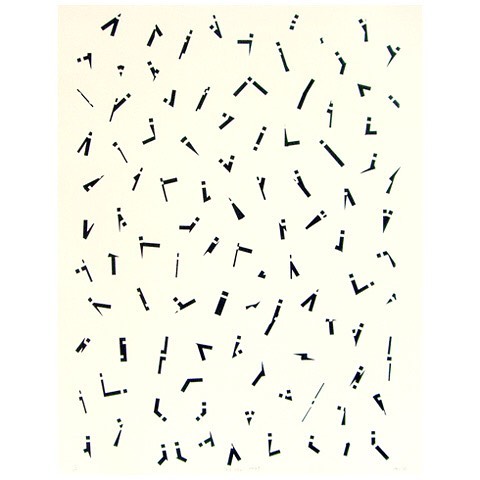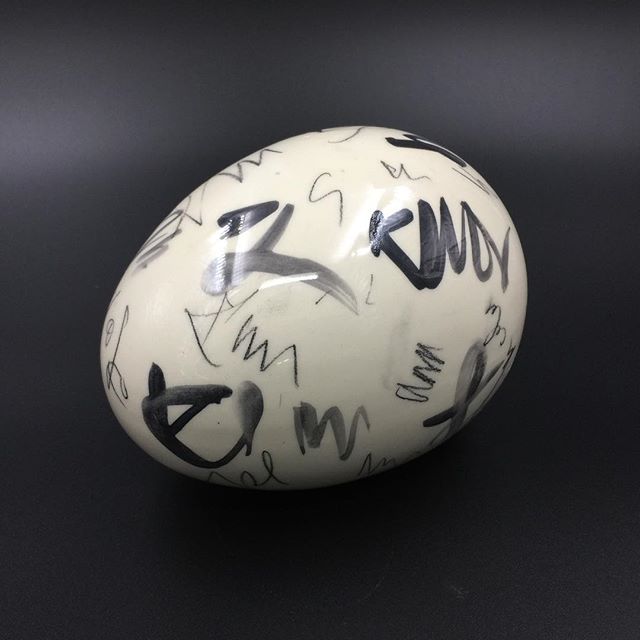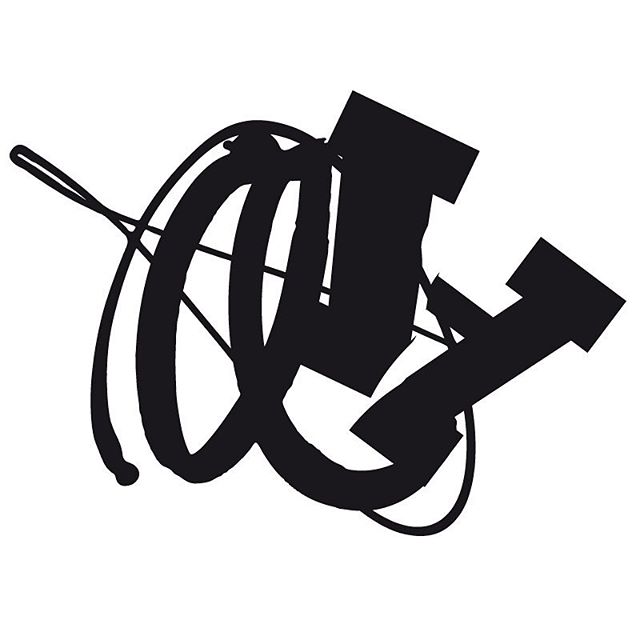
Schrift und Bild – faszinierende künstlerische Interpretationen eines jahrhundertealten Themas: die Schrift als eigenständiger künstlerischer Bildinhalt. Der Verein Schrift und Bild e.V. und die gemeinnützige Stiftung Schrift und Bild präsentieren ausgewählte Künstler mit ihren Positionen. Inspirierende Kunstprojekte, einzigartige Editionen und ein bedeutendes Erbe: seit 2008 feiern wir die konkrete und visuelle Poesie.
Im Jahre 1963 kuratierte Dietrich Mahlow (1920-2013) die Ausstellung »Schrift und Bild« in der Staatlichen Kunsthalle Baden-Baden und im Stedelijk Museum Amsterdam. Ein gleichnamiger Katalog erschien. Er versammelte künstlerische Positionen zwischen Schrift und Bild, Geste und Zeichen. Das Logo als Buchtitel dazu schuf der Grafiker Wolfgang Schmidt (1929-1995), ein bedeutender Vertreter der Kasseler Schule der Plakat- und Buchkunst und der künstlerischen Grafik. Es zeigt ein Wesensmerkmal der Richtung »Schrift und Bild«: eben ein Bildmotiv, das aus Schrift besteht.
2008 machten sich engagierte Kunstinteressierte auf und gründeten rund um das Werk von Franz Mon (1926–2022 in Frankfurt) und seinem Schüler Jörg Schmitz (*1969 in Hannover) eine Initiative mit dem Ziel, Kunst und Künstler der visuellen und konkreten Poesie zu fördern. Ihre langfristige Vision:
EIN MUSEUM FÜR SCHRIFT UND BILD.
Die Vision von einem Museum, ebenso wie die Vorstellungen und Möglichkeiten der Präsentation von Werken der bildenden Kunst, haben sich gerade in den letzten 10 Jahren stark gewandelt – die Digitalisierung macht vieles möglich.
Diesen neuen Vorstellungen, »Schrift und Bild« zu bewahren, zu fördern und weiterzuentwickeln haben sich Verein und Stiftung Schrift und Bild mit ihrer ständig wachsenden Sammlung und ihrem nachhaltigem Engagement leidenschaftlich verschrieben – seit 2021 in der Errichtung des
Outdoor-Museums der Poesie und der Kunstroute Main-Kinzig.